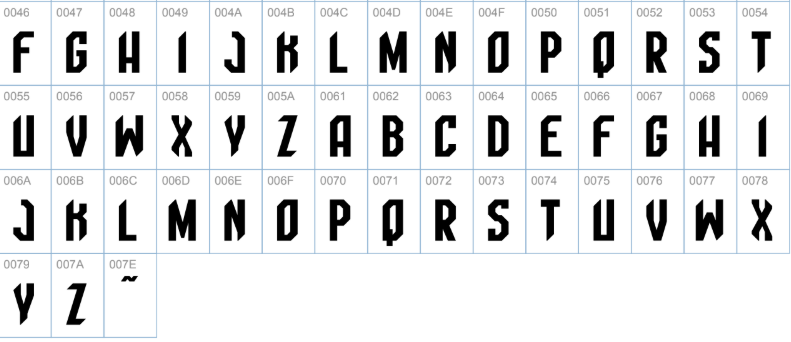
Uma nova era começou em São Januário. A temporada 2026 marca a estreia do lendário “Swoosh” da Nike no peito do Vasco da Gama, trazendo uma identidade visual globalizada para o Gigante da Colina.
A troca de fornecedor impactou diretamente o design dos números e nomes, que agora seguem os padrões tecnológicos da marca norte-americana, sem perder a essência cruzmaltina. Neste post, você baixa a tipografia exata utilizada nos novos uniformes para aplicar em seus projetos.
Estilo Visual da Tipografia
A Nike trouxe para o Vasco em 2026 uma fonte com design limpo, minimalista e de alta legibilidade, característica dos seus principais clubes globais. Diferente dos estilos mais rococós ou serifados de anos anteriores, a nova tipografia aposta em linhas geométricas puras e espessura média.
Esse visual moderno cria um contraste interessante com a tradicional Faixa Diagonal, modernizando o kit sem desrespeitar a história. Os números possuem cortes internos estratégicos que garantem respirabilidade na camisa de jogo e um visual agressivo nas aplicações digitais.